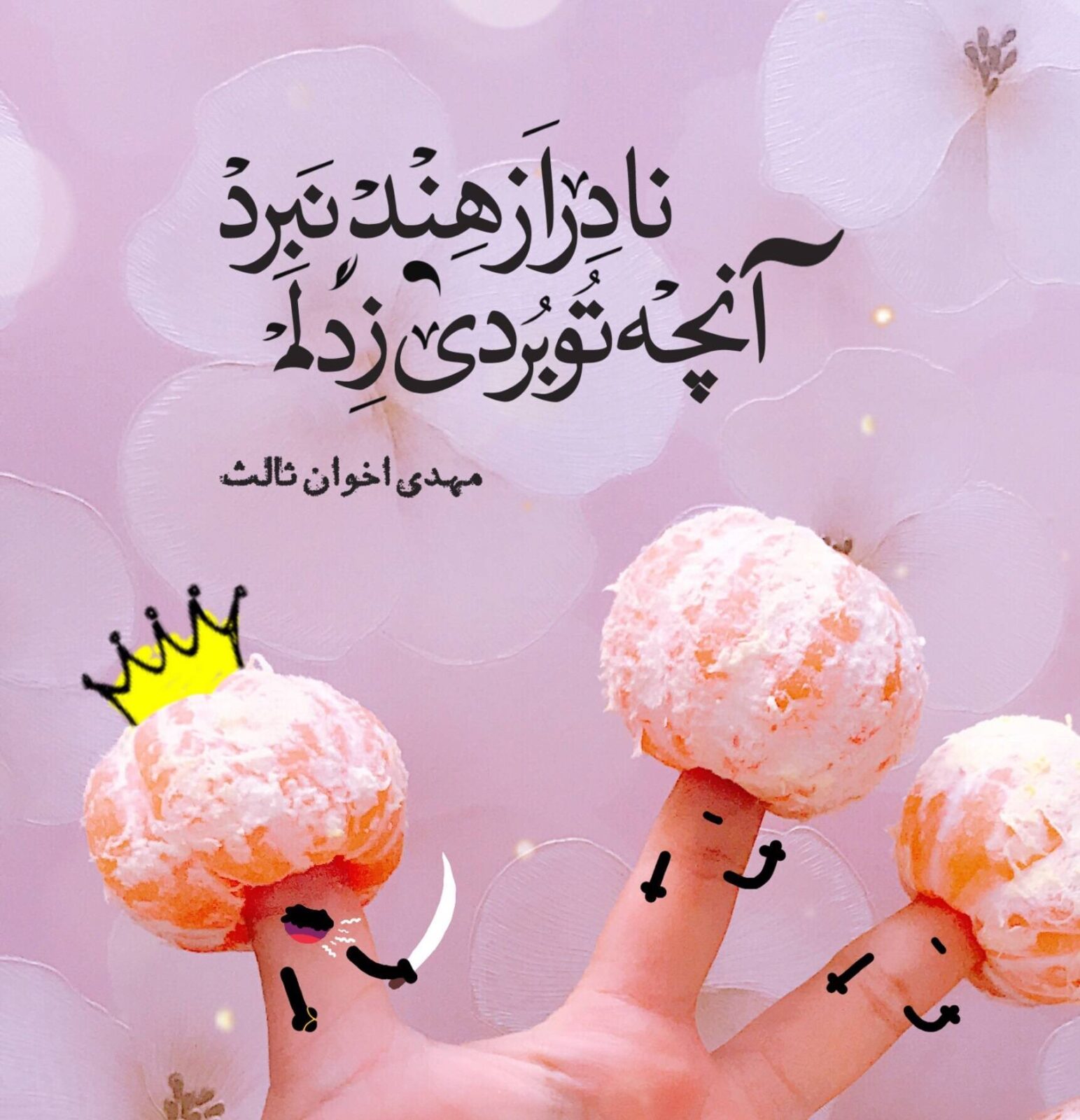
عکس نوشته با فونت ادوبی نسخ - Adobe Naskh
یکی از فونت های خوبی که بارها و بارها درباره آن از من سوال شده است و میشود همین فونت ادوبی نسخ Adobe Naskh است. فونت ادوبی نسخ یک فونت نسخ متوسط بسیار با کیفیت و شامل صدها حرف ترکیبی که زیبایی خاصی به آن داده است.
فونت ادوبی نسخ
فونت ادوبی نسخ در طرح های عکس نوشته نیز بسیار استفاده میشود و جزو فونت های محبوب به شمار می آید. این فونت تک وزن که بر پایه خط نسخ طراحی و پیاده سازی شده است در سال 2011 توسط شرکت بزرگ ادوبی برای نخستین بار منتشر گردید.
فونت ادوب نسخ از تمام حروف فارسی، عربی، اردو، کردی پشتیبانی میکند و همچنین تمام حروف لاتین هم وزن و هم اندازه ای در خود دارد. حروف عربی فونت ادوبی نسخ توسط خطاط پاکستانی محمد زهیر روحانی بازی (Muhammad Zuhair Ruhani Bazi) و حروف لاتین آن توسط Robert Slimbach طراحی و پیاده سازی شده است.